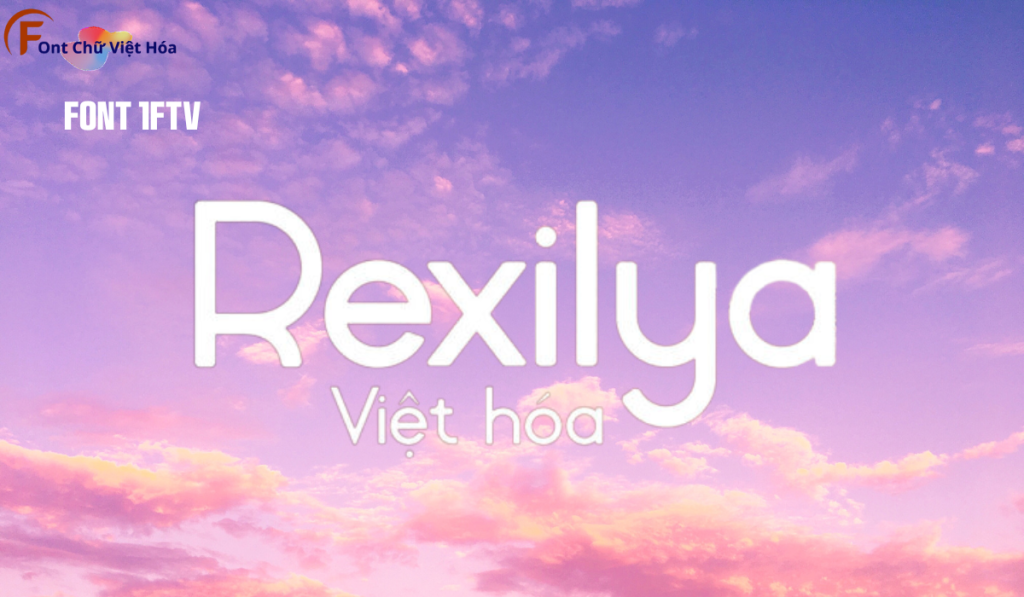
Font 1FTV Rexilya
Độ dày: Thường, Đậm
Font 1FTV Rexilya là một font chữ độc đáo, thuộc bộ 1FTV, nổi bật với phong cách sans-serif hiện đại và các đường nét mềm mại, tinh tế. Thiết kế của 1FTV Rexilya tập trung vào sự thanh lịch và dễ đọc, đặc biệt phù hợp cho các thiết kế đòi hỏi tính thẩm mỹ cao như poster, logo, và tiêu đề. Với tỷ lệ chữ cân đối và các đường nét rõ ràng, font này tạo ra ấn tượng thị giác mạnh mẽ và giúp tối ưu hóa không gian trong thiết kế. Font này cũng đã được Việt hóa, mang đến sự linh hoạt và tiện dụng cho các dự án thiết kế bằng tiếng Việt.